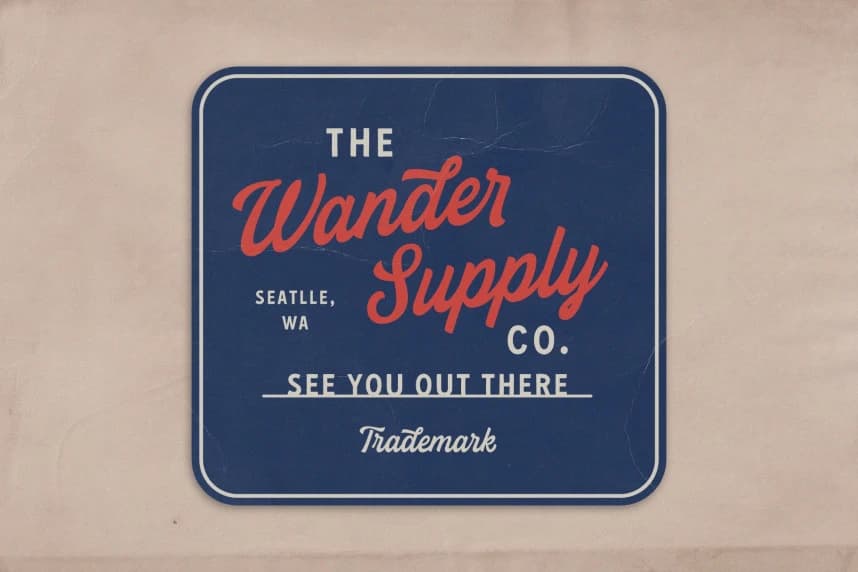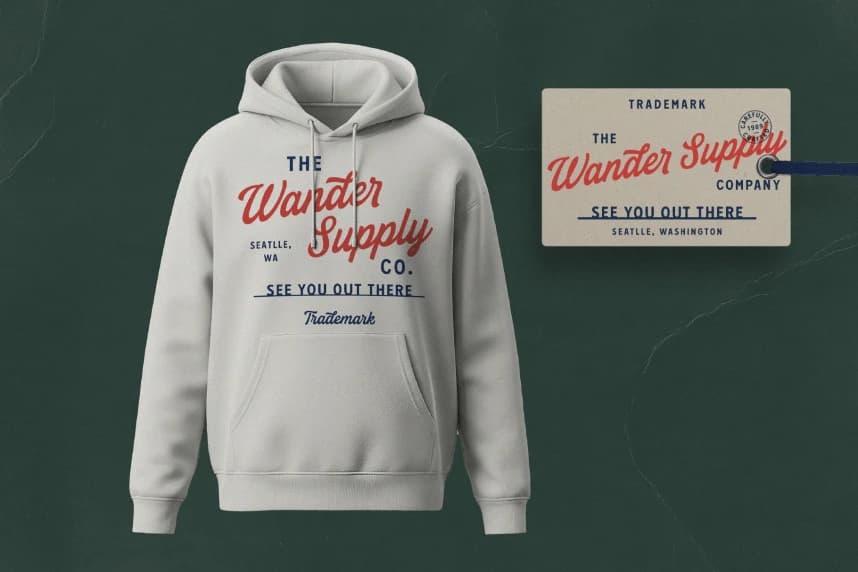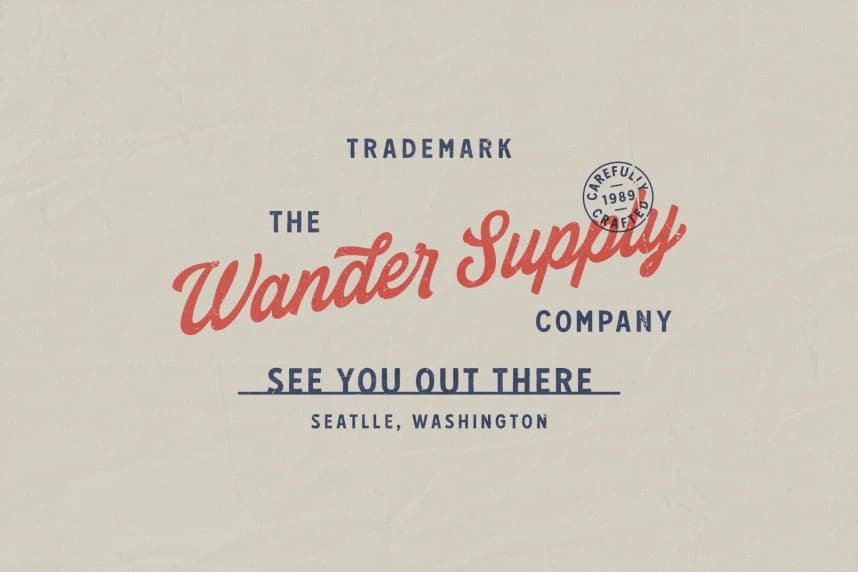
RD Landford Script Font! Landford, oyun tadında fakat çarpıcı, temiz bir fırça yazı tipidir. Kalın, el çizimi harf biçimleri, hafif eğlenceli ürün tasarımları, marka kimliği projeleri, logolar, ev eşyası tasarımı, ürün ambalajı, yazı kompozisyonları, tişörtler veya m
RD Landford Script Font! Landford, oyunlu ama çarpıcı, temiz bir fırça yazı tipi. Kalın, elle çizilmiş harfleriyle, neşeli ürün tasarımları, marka tasarımı projeleri, logolar, ev eşyası tasarımı, ürün ambalajı tasarımı, harf yazımı kompozisyonları, tişörtler veya daha etkili alıntı tasarımları üzerinde öne çıkması garanti edilir.